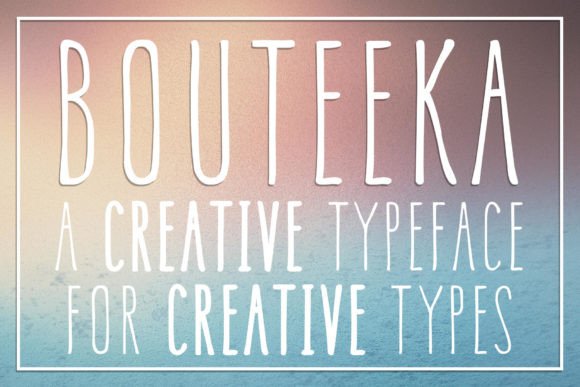
Bouteeka
Mencari elemen reka bentuk yang sesuai boleh menjadi mencabar, tetapi Bouteeka menawarkan koleksi luar biasa yang menaik taraf karya anda serta-merta.
Dicipta dengan ketepatan, Bouteeka menyediakan vektor yang bersih, tipografi yang licin dan lesen komersial untuk ketenangan fikiran.